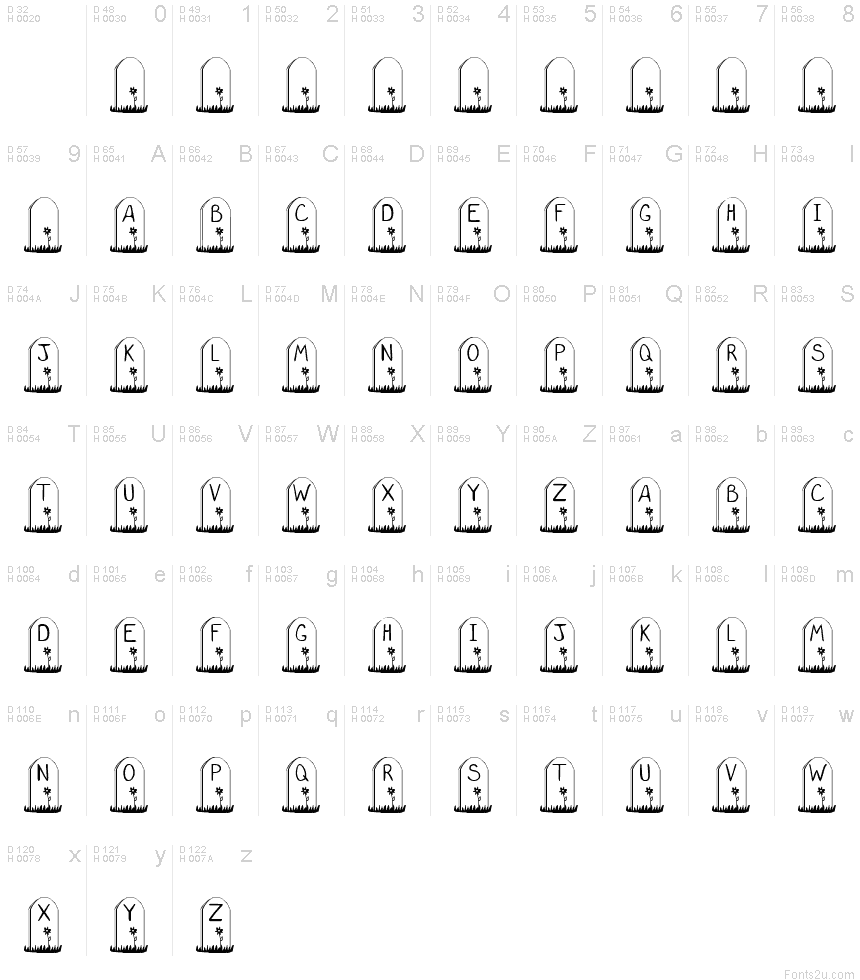
KR Gravestone, da Katsfunfonts, é uma fonte decorativa display feita a partir de lápides arqueadas, com as letras encaixadas em cada pedra, além de um pequeno broto e um pedaço de grama na base. Cada glifo repete o mesmo contorno de lápide, com o detalhe da pequena flor e da grama unindo toda a família.
KR Gravestone combina com convites de Halloween, flyers de casas assombradas, peças de memorial, pôsteres de festas e títulos de scrapbook que pedem uma referência direta a cemitérios. Também funciona bem em aberturas de capítulos, sinalizações sazonais e textos curtos em banners, onde as lápides arqueadas fazem quase todo o trabalho visual.